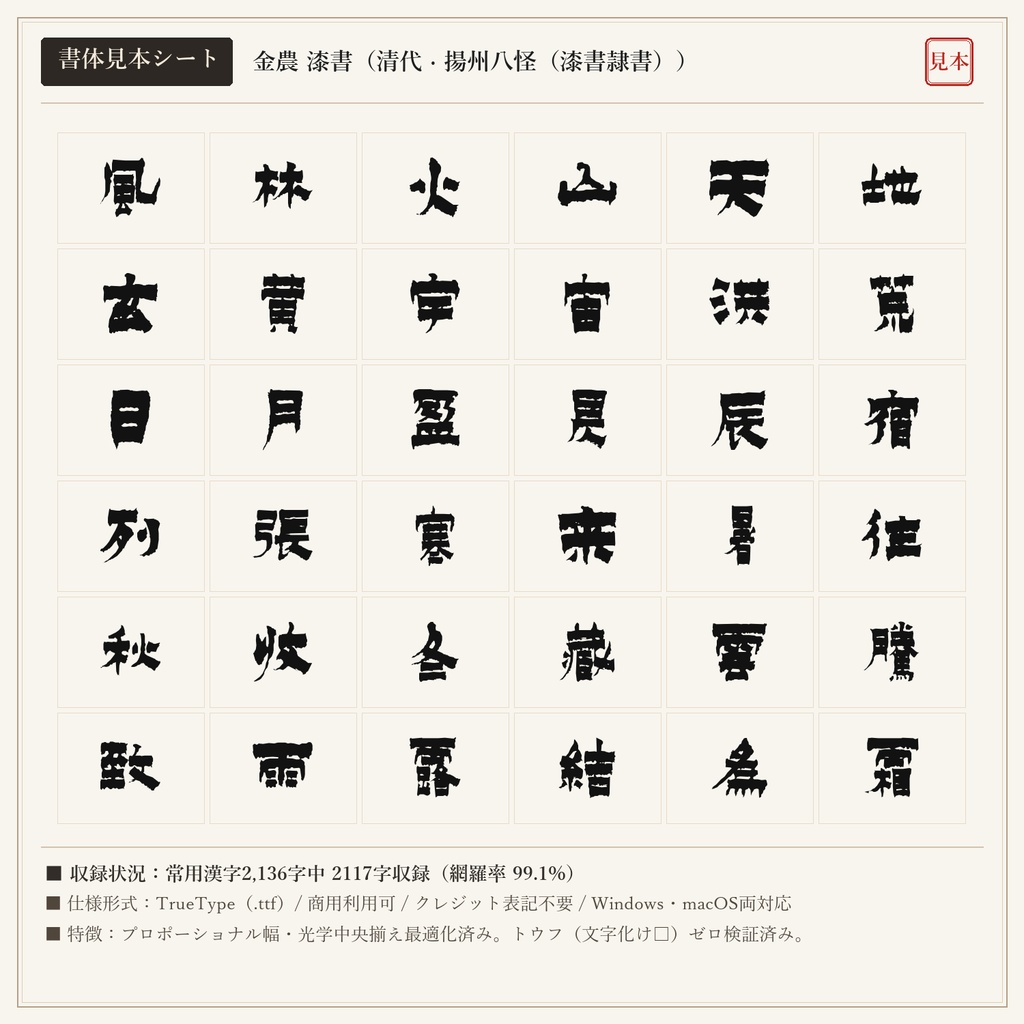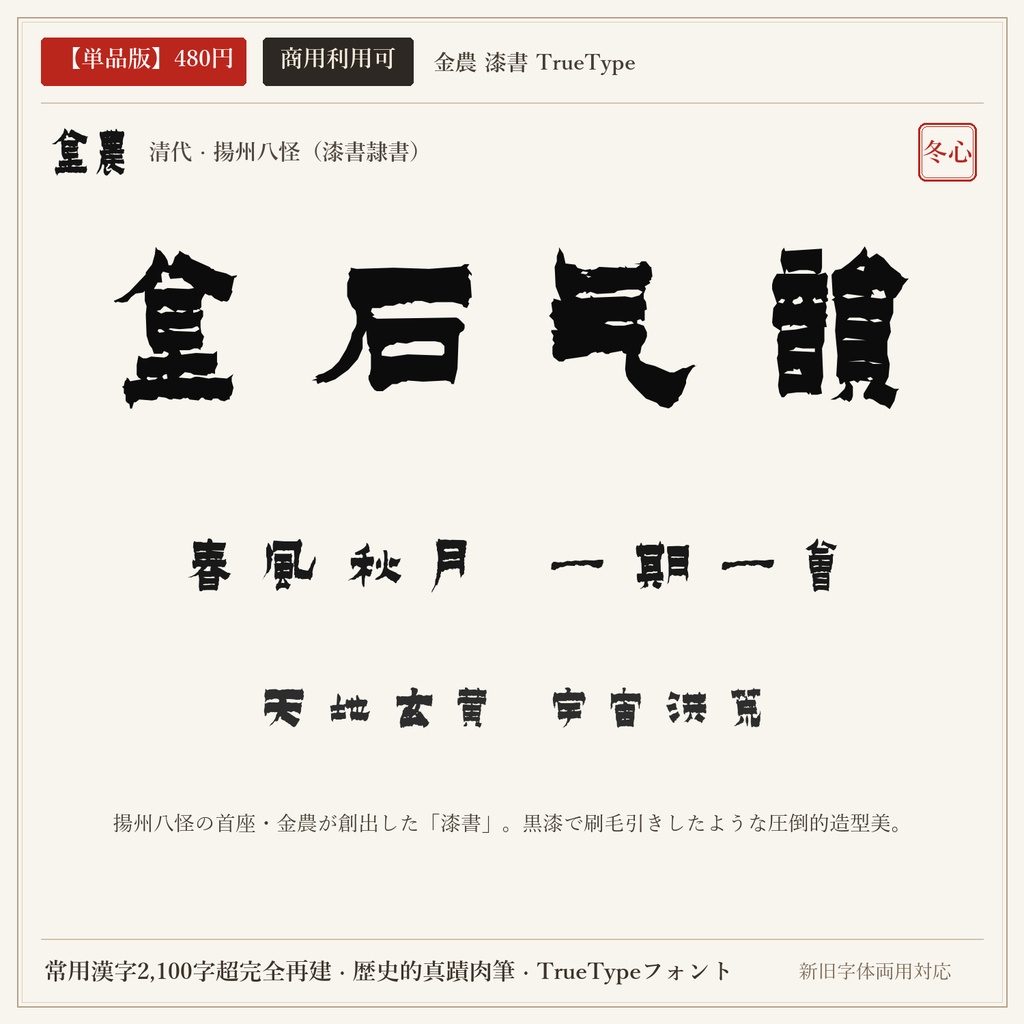
清代屈指の独創書家・金農の「漆書」から輪郭抽出した隷書フォントです。羊毛の筆を平らに切り落とし、黒漆を刷毛で塗りつけたような截頭截尾の極太直線と古朴な重厚感は、他に見られない強烈な存在感を放ちます。 ■ 本フォントの特徴 ・常用漢字2,136字中、2117字を高精度収録(網羅率 99.1%)。 ・現代の新字体を入力しても、歴史的な真蹟字形・旧字体が自然に出力されるデュアルマッピング対応。 ・文字ごとの最適なプロポーショナル字幅設定により、自然で流麗な連綿と墨の息遣いを再現。 ・トウフ(文字化け□)を出さない事前フォントマッピング検証済み。 ■ 未収録文字一覧(全19字) 歴史的真蹟・拓本に存在しない以下の字種は未収録(非対応)となります。ご購入前にご確認ください。 刹 厘 唄 堀 峠 扱 拶 枠 栃 桁 濫 碁 線 繰 脊 菓 著 込 酎 ■ 形式 TrueTypeフォント(TTF) / Windows・macOS両対応 ■ 利用規約 個人・法人の商用利用OK。クレジット表記不要。 ロゴ、動画、ゲーム、書籍、同人誌、配信サムネイル、Web、印刷物、グッズ等に自由にご使用いただけます。 フォントファイル自体の再配布・共有・販売・転売は禁止です。 ※東晋の王羲之(行書)と盛唐の顔真卿(楷書)を同梱した「【無料版】王羲之 + 顔真卿 2書体セット(0円)」もショップ内にて無料配布中です。